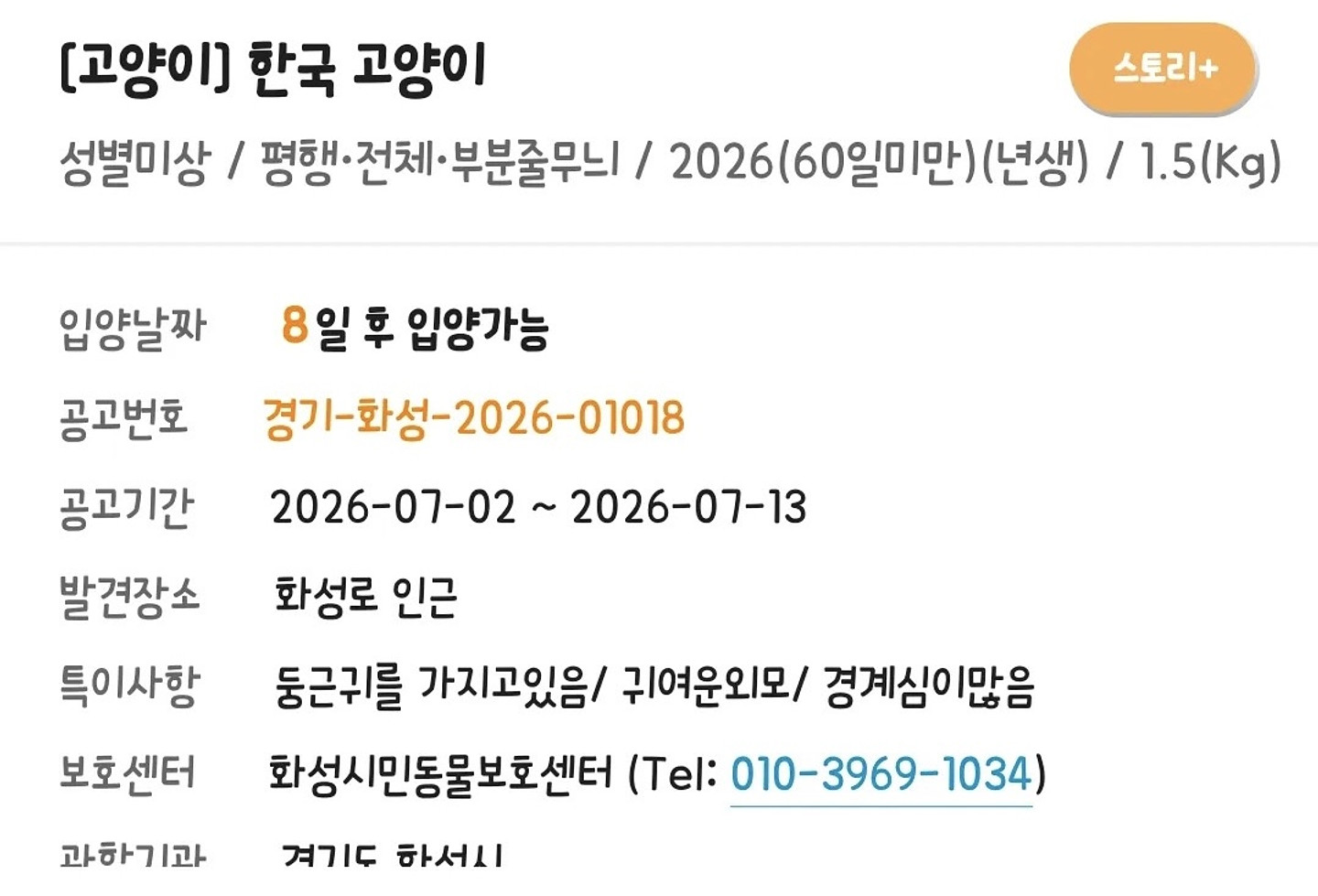
lg스마트체 라고 하는데 혹시 이것과 비슷한 폰트 없을까요 ㅜㅜ 얘는 상업적 이용불가라 유료라도 좋으니 비슷한 폰트를 찾고 싶습니다.
어떤 폰트 일까요ㅜㅜ?
뾰족한 모서리랑 ㅅ의 획 구분이 특징이에요
혹시 해당 폰트 이름 아시는 분 계세요?
뭘까요?? 혹시 영어 폰트도 아시면 같이 알려주시면 감사하겠습니다!!!
이 폰트가 뭔지 궁금합니다
제가 동그라미 친 부분 폰트는 무슨 폰트인가요?
폰트 알려주세요!
카톡테마 블로그 구경하다가 이 폰트가 너무너무 예뻐서요ㅠㅠ 무슨 폰트인지 알 수 있을까요?? 고딕같은데..
이거 뭘까용~??
이 글씨체 뭔지 아시는분 있으실까요? ㅠ
모닝스페셜 무슨 폰트일까요 ㅠㅠ
이 폰트 뭘까요?.. 비슷한거라도 있을까요
이 폰트 알수있을까요? 비슷한 느낌이라도
이게 어떤 서체인지 알 수 있을까요???